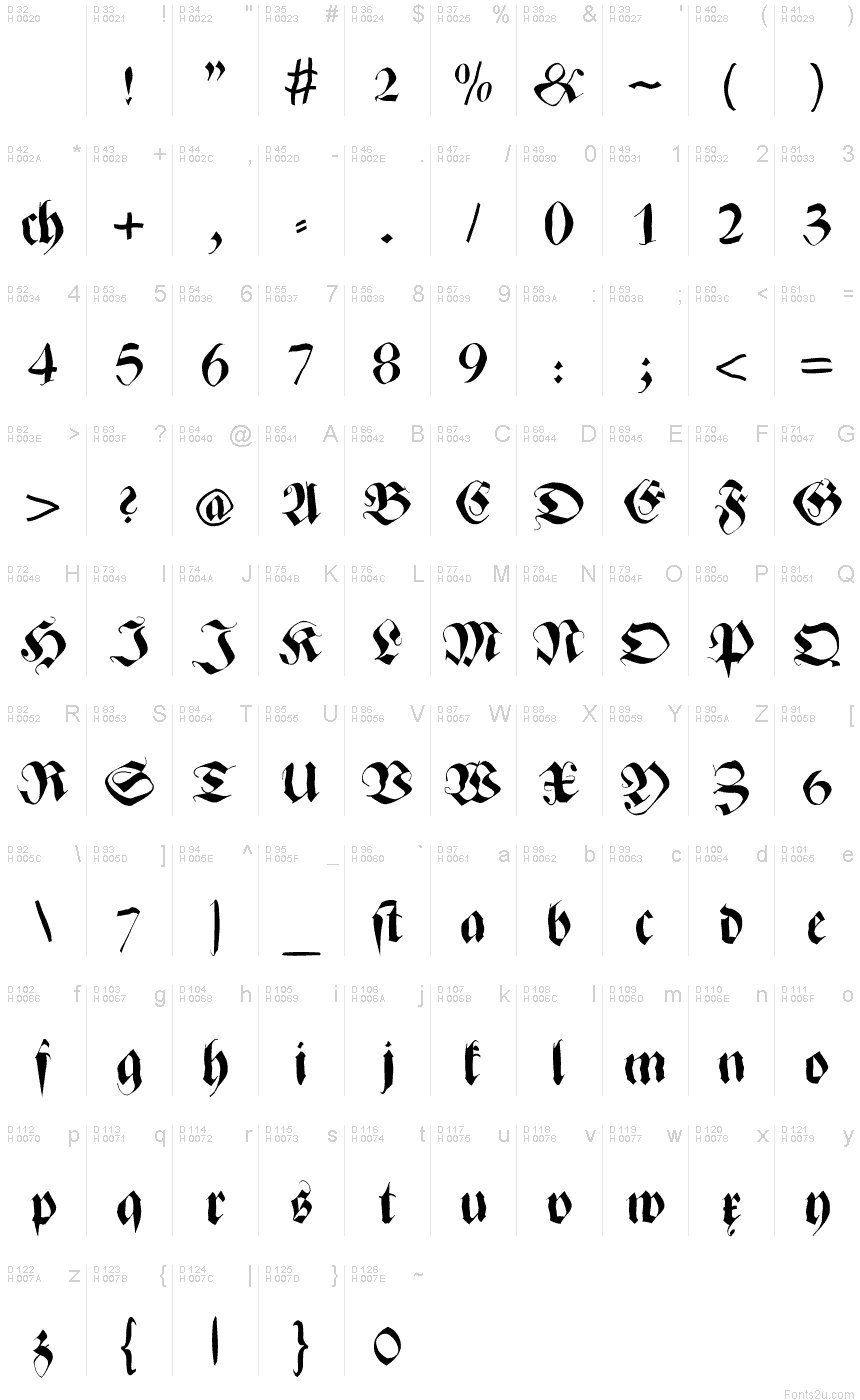
Zen Frax Freestyle autorstwa M. Kleina to darmowy, średniowieczny krój pisma typu blackletter o dostojnym, ceremonialnym charakterze. Litery opierają się na klasycznych gotyckich kątach i łamanych krzywiznach, ale prawdziwym atutem są tu bogate zdobienia – haczykowate początki, wstążkowe zawijasy i długie ogonki, które nadają wielkim literom wygląd stworzony do heraldycznych tytułów, a nie zwykłego tekstu.
Świetnie sprawdzi się na plakatach, okładkach albumów i książek, ulotkach wydarzeń oraz w brandingu, który wymaga liturgicznego, starodawnego klimatu. Jako darmowy font, najlepiej prezentuje się w krótkich hasłach, gdzie te zapętlone kreski mają przestrzeń, by wybrzmieć. Wykorzystaj go w tytułach, przy rozpoczynaniu rozdziałów lub w formie monogramów, gdy zależy Ci na dramatycznym efekcie bez rezygnacji z tradycji blackletter.